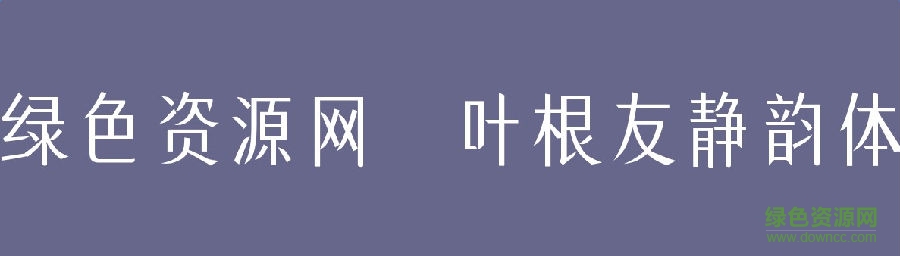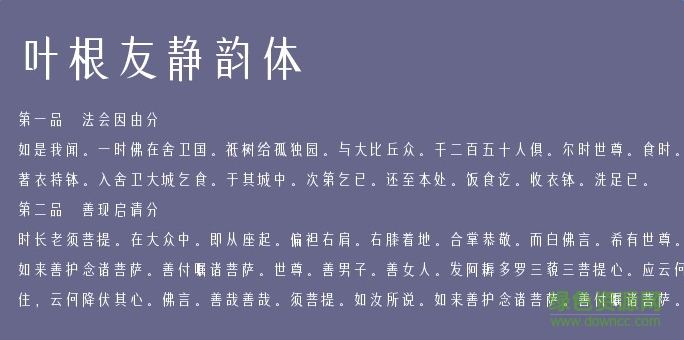
葉根友靜韻體字體
葉根友靜韻體是一款由知名書法家葉根友創(chuàng)造的字體,比劃圓潤,適用于廣告、藝術(shù)設計,海報設計等方面,有需要的朋友們不要錯過了。歡迎大家來綠色資源網(wǎng)踴躍下載哦!
葉根友靜韻體是一款時尚的中文字體,字形的筆畫設計在傳統(tǒng)的基礎(chǔ)上有許多創(chuàng)新的變化,追求圓潤與剛毅中互相取意,葉根友靜韻體是一款適合應用與廣告設計、標題以及相關(guān)時尚類排版的應用。